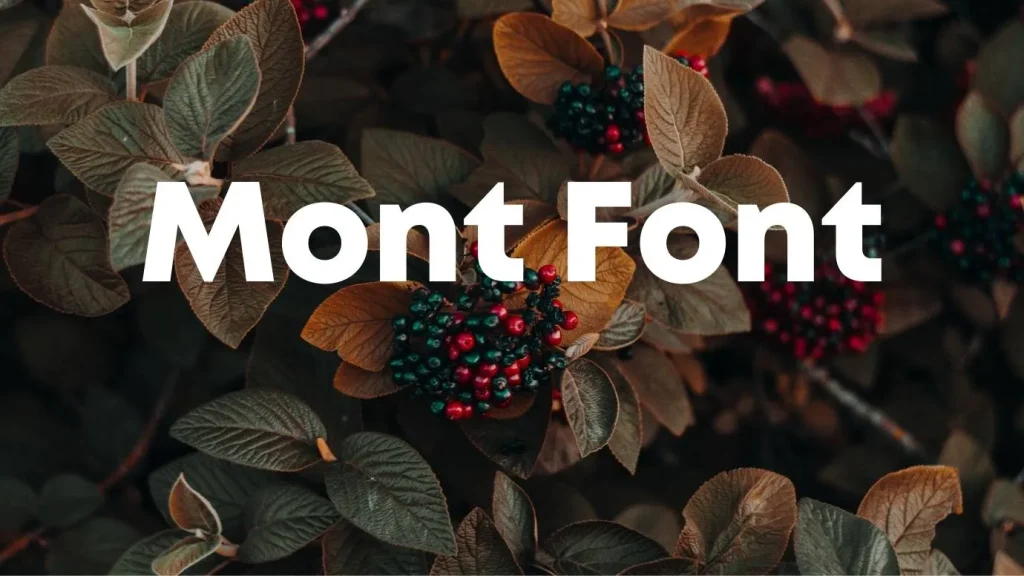
Mont Font là một trong những phông chữ nổi bật trong thiết kế đồ họa hiện đại, được yêu thích bởi sự thanh lịch và dễ đọc. Với thiết kế gọn gàng, Mont font là font chữ thuộc bộ font chữ không chân, mang lại sự tinh tế và chuyên nghiệp cho mọi dự án từ in ấn đến thiết kế kỹ thuật số. Phông chữ này đặc biệt phù hợp cho những ai muốn tạo ra các sản phẩm sáng tạo có tính thẩm mỹ cao mà vẫn đảm bảo tính khả dụng. Nếu bạn đang tìm kiếm một phông chữ đa năng, Mont Font chắc chắn là một lựa chọn không thể bỏ qua.